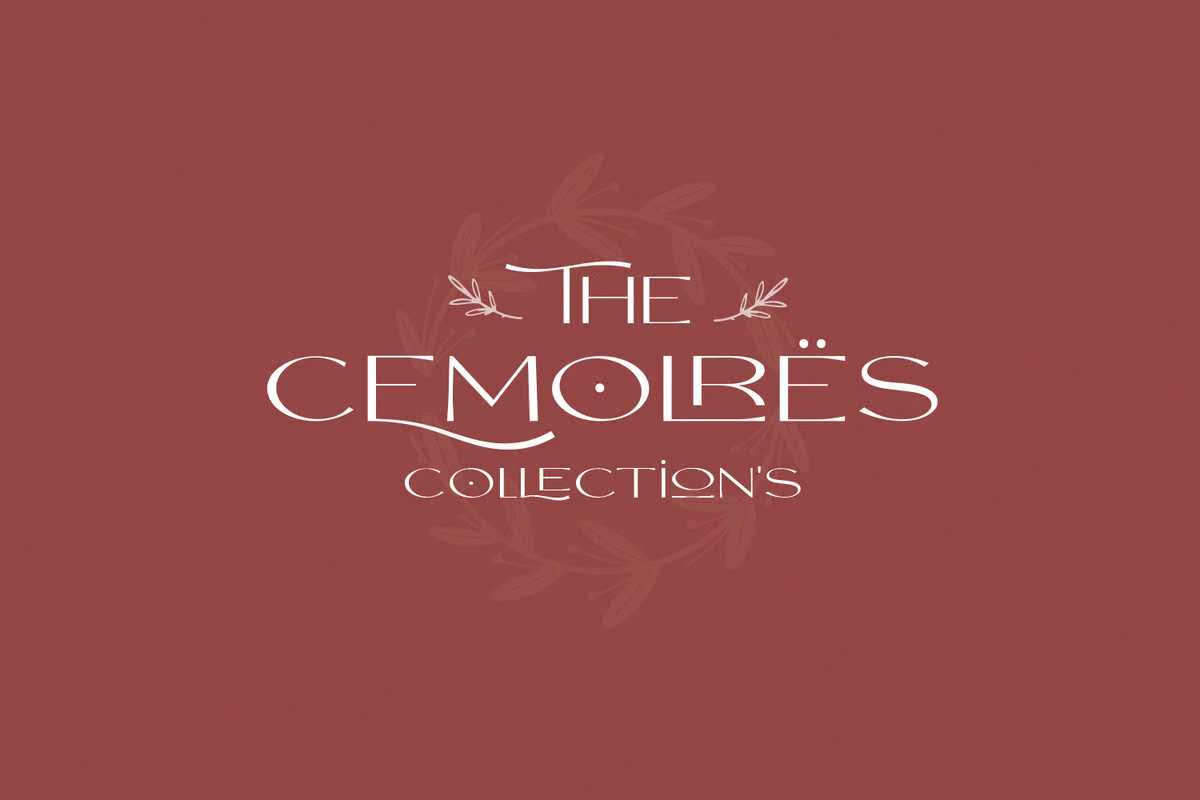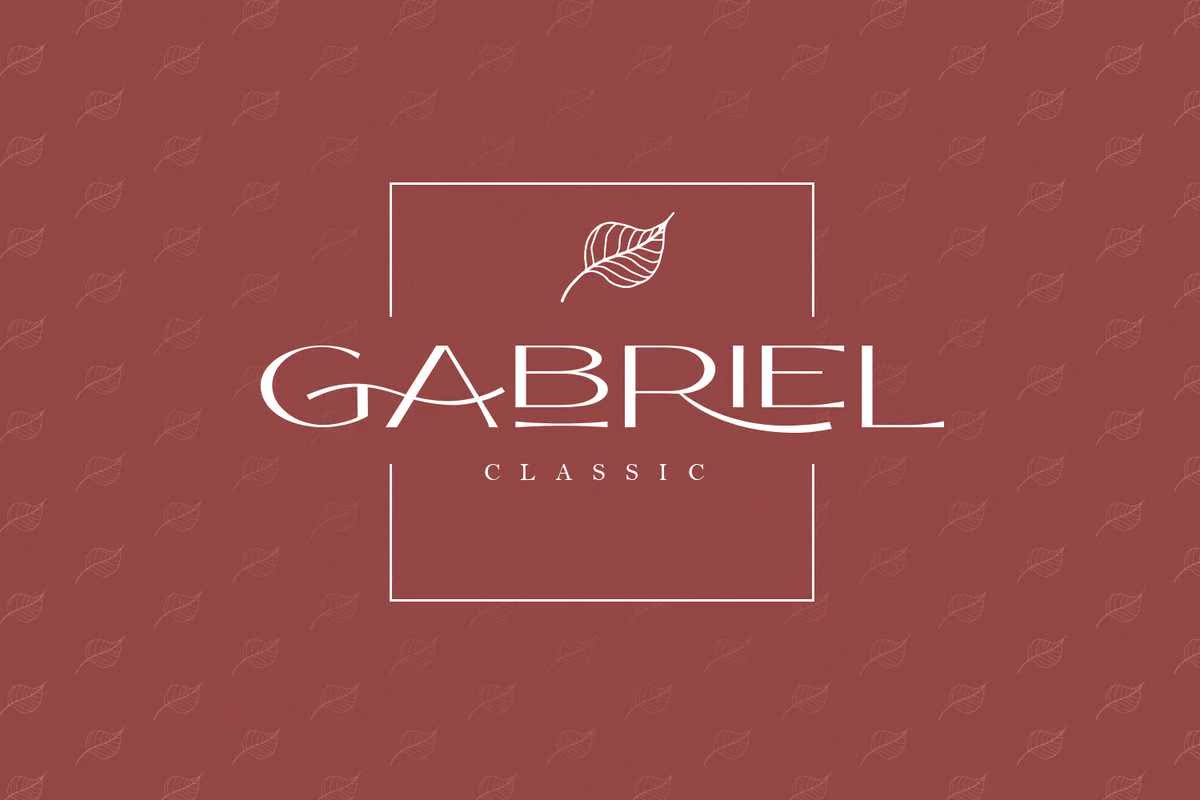
RollgatesVictoriaFont真有趣!在我所设计的所有内容中,这是一件非常有趣的事。轻巧的装饰真的很适合你,希望你也能喜欢!你不会发现像这样的曲线是不规则的。现代是经典的,简约是装饰性的。看看数字…然后再看看。它们的曲线有点不寻常的地方。如果你想突出这是你的风格。logoortle,fashion distribution masthead,monogramorInstagram,用这个字体创造美丽。rollgates v pictorafont candoit-RollgatesVictoriaFont真有趣!在我所设计的所有内容中,这是一件非常有趣的事。轻巧的装饰真的很适合你,希望你也能喜欢!你不会发现像这样的曲线是不规则的。现代是经典的,简约是装饰性的。看看数字…然后再看看。它们的曲线有点不寻常的地方。如果你想突出这是你的风格。logoortle,fashion distribution masthead,monogramorInstagram,用这个字体创造美丽。rollgates v pictorafont candoit-